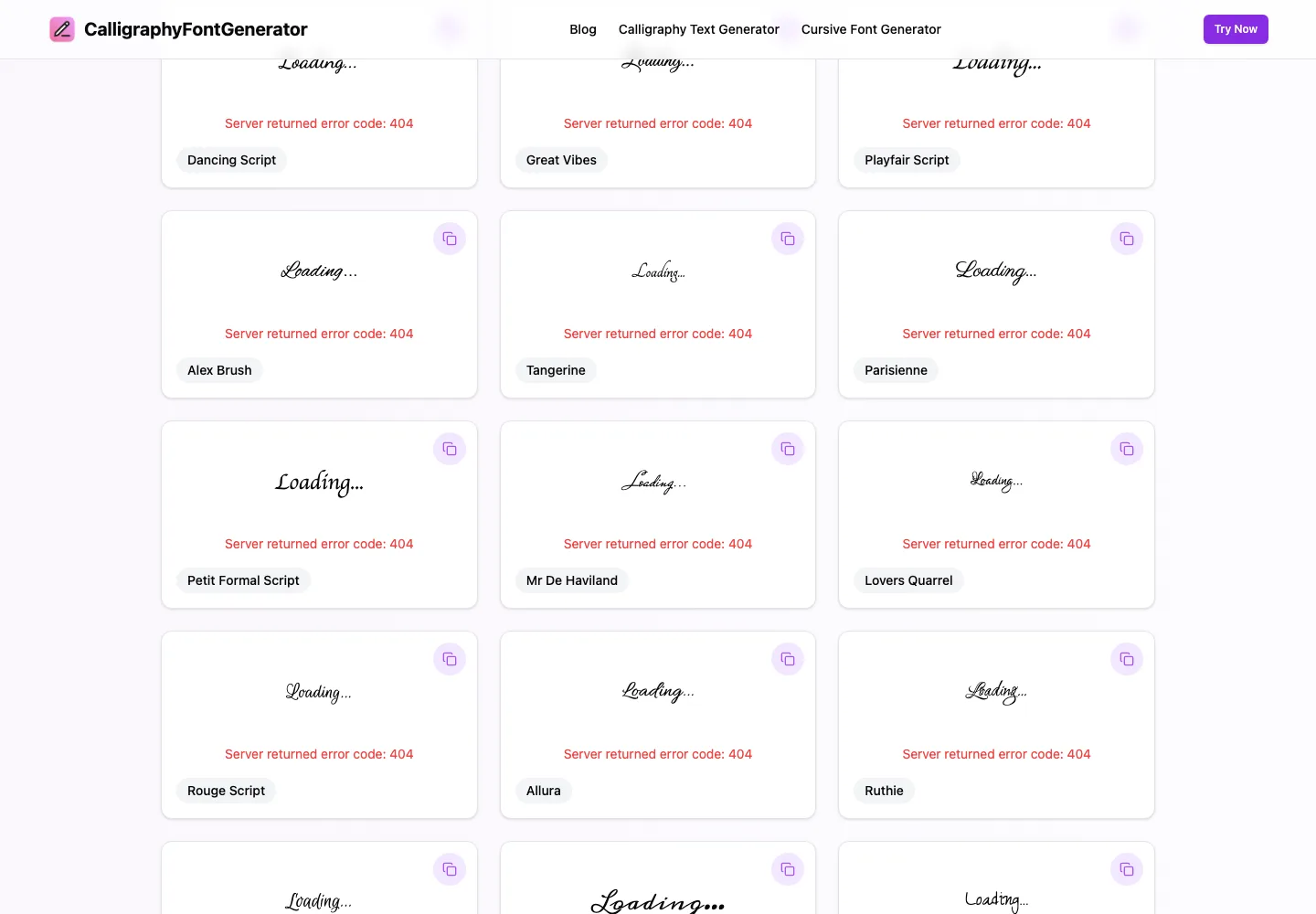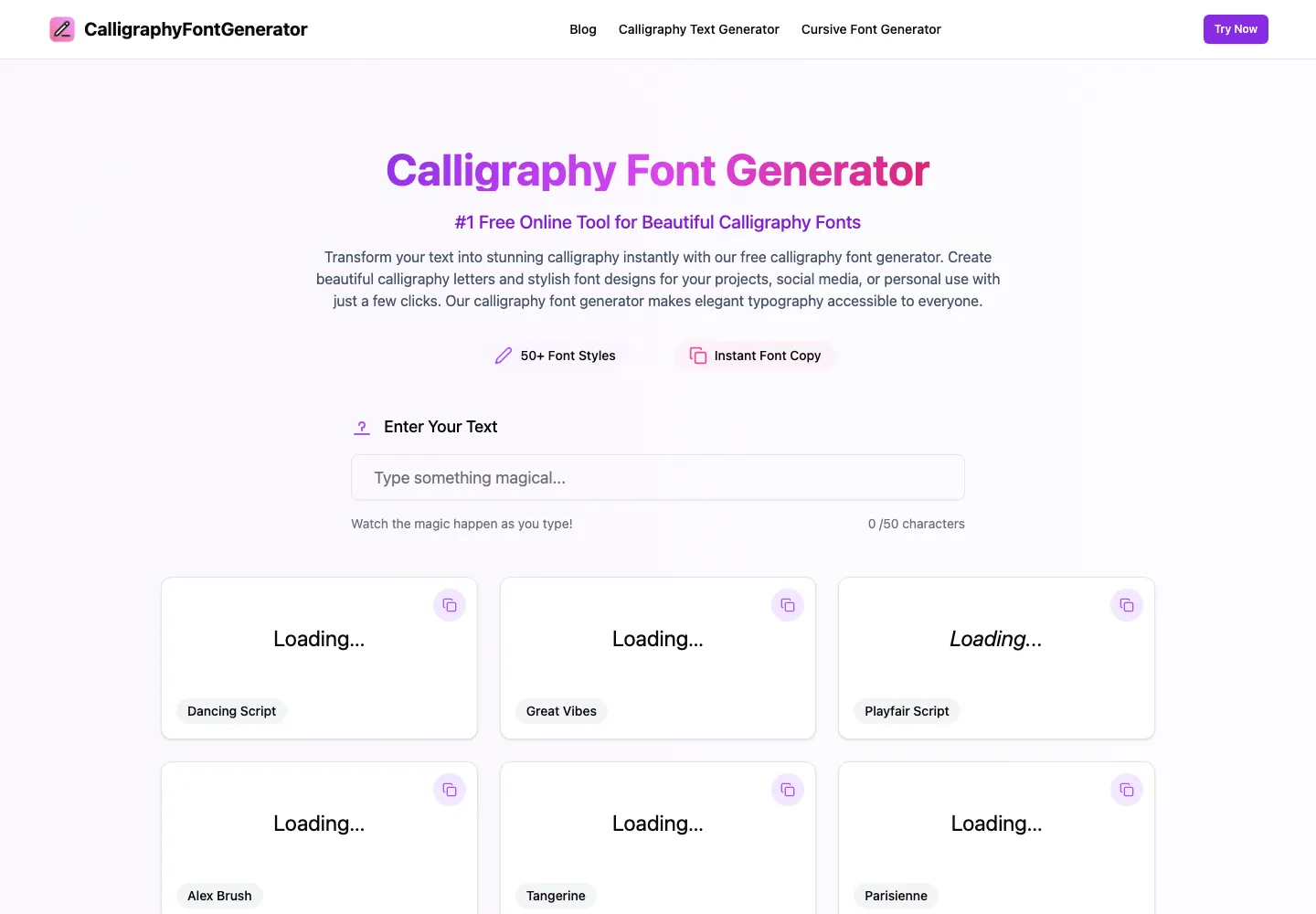
Calligraphy Font Generator 實測:字體全借自 Google Fonts
calligraphyfontgenerator.org 打著 50 多種書法字體、AI 推薦與圖片匯出的招牌,2026 年 9 月實測預覽功能整組 404,原始碼裡的字體清單只有 24 個,其中 23 個直接來自 Google Fonts。這篇整理實測經過、文案與程式碼的落差,以及直接去源頭下載字體的替代路線。
搜尋「書法字體產生器」,很容易撞上 calligraphyfontgenerator.org 這個站:招牌寫著 50 多種書法字體、即時預覽、PNG/JPG/SVG 匯出,還有 AI 字體推薦與簽名產生器。我在 2026 年 9 月 13 日實際打開它、輸入文字測了一輪,得到的結論跟文案落差很大:字體預覽功能整個是壞的,24 張預覽卡全部回 404 錯誤;文案寫的 50+ 字體,在它自己的程式碼裡只有 24 個;至於匯出圖檔、AI 推薦這些招牌功能,在整個網站公開的前端程式碼裡都找不到實作。
我打開網站輸入文字,24 張預覽卡全部回 404
實際使用的方式很單純:首頁有一個輸入框,上限 50 個字元,打完字之後,下方會展開一整排字體預覽卡,每張卡用不同字體渲染你輸入的文字,右上有 Copy 按鈕。流程設計本身沒問題,問題出在它此刻跑不起來。
我用瀏覽器實測,同一個下午試了首頁與兩個子頁面、多次重新載入,結果一致:預覽卡全部停在「Server returned error code: 404」的紅字,輸入什麼字都不會出現預覽。直接呼叫它背後的預覽 API,得到的也是 Apache 伺服器回的 404,代表這個 API 在伺服器端根本沒有在跑,與我這邊的網路環境無關。首頁還有另一個毛病:頁面載入時觸發 React 的編號 329 錯誤,運氣不好時整頁直接變成「Application error」白畫面,運氣好時互動區勉強活著,但字體卡一樣全壞。
Calligraphy Font Generator 字體預覽卡截圖,每張卡顯示字體名稱與 Copy 按鈕,卡內出現紅色 Server returned error code 404 錯誤文字,預覽停留在 Loading 狀態Pin
2026 年 9 月實測:24 張字體預覽卡全部停在 404 錯誤,輸入文字不會出現預覽(圖片來源:Calligraphy Font Generator 官網截圖)
預覽掛掉時,Copy 按鈕的行為也值得知道。從它公開的前端程式碼看,這個按鈕複製的內容有兩層:API 正常時複製轉換過的花俏文字,API 失敗時退回把你輸入的原文原封不動複製回剪貼簿。也就是說,現在按下 Copy,你只會拿回自己剛打的那幾個字,等於沒複製到任何東西。
就算未來 API 修好了,這類「複製文字」的產生器還有一個先天的上限:它複製出來的是文字內容,美麗的書法外觀取決於你貼過去的軟體有沒有安裝那套字體。把花俏文字貼進 WhatsApp 或 Instagram,對方看到的通常只是普通字型,因為那些 App 沒有 Dancing Script 這套字體可套用。要讓作品在任何地方都長得一樣,正解永遠是把成品輸出成圖片,或者拿到字體檔本體,而這兩件事這個站都做不到。
這裡要誠實畫一條線:以上是單一時點的實測結果。我在同一天多次載入、走不同頁面、直打 API,結論都一致,但站方什麼時候把伺服器修好,我不知道。如果你讀這篇文章的時間距離 2026 年 9 月已經很久,值得自己再開一次網站驗證,別把這篇的「現在壞了」當成永久判決。
文案寫 50+ 字體,程式碼裡的清單是 24 個
「50+」的字樣在首頁多處出現:統計卡寫「50+ Font Styles」,功能標題寫「50+ Elegant Fonts」,FAQ 也寫著「all 50+ fonts」。但把網站載入的 JavaScript 檔案抓下來看,字體清單是一個寫死的陣列,編號從 1 排到 24:Dancing Script、Great Vibes、Alex Brush、Tangerine、Parisienne,一路到 Sacramento,中間沒有動態載入的第五十個。頁面實際渲染出來的預覽卡,也確實就是 24 張。
Calligraphy Font Generator 官網首頁截圖,標題寫著第一名的免費線上書法字體工具,宣稱 50 以上字體風格,下方為文字輸入框與字體預覽卡Pin
官網首頁掛著 50+ Font Styles 的招牌,實際字體清單是 24 個(圖片來源:Calligraphy Font Generator 官網截圖,2026 年 9 月)
24 個裡面還有一個特別的:「Playfair Script」。這個名字在 Google Fonts 查不到對應字體(API 直接回 400),而網站自己的樣式表把它對應到 Playfair Display 這個襯線字體的斜體。換句話說,那張卡片顯示的既不是它宣稱的名字,也不太算書法字體。
其他招牌宣稱也對不上。首頁的功能區塊列了 PNG/JPG/SVG 多格式匯出、AI 字體推薦、簽名產生器、字體配對工具,FAQ 還說註冊帳號能收藏字體。我把整個網站公開的前端程式碼全部掃過一遍:沒有任何下載圖片或轉 SVG 的程式碼,沒有任何推薦邏輯,簽名與配對也沒有對應頁面,站內地圖總共 18 條網址,沒有一條是這些功能。註冊入口同樣不存在,login、signup 這些路徑全是 404。服務條款裡寫的帳號、付款、退款,在站上找不到任何對應的東西。
網站宣稱實測與原始碼
50+ 種書法字體清單寫死 24 項,其中 1 項對不到真實字體
PNG/JPG/SVG 匯出前端程式碼與站內頁面都找不到實作
AI 字體推薦無推薦邏輯,無對應頁面
簽名產生器、字體配對工具無對應頁面
註冊帳號收藏字體無任何註冊入口
數千名滿意用戶見證見證者引言把站名叫成 CalliGen Pro,與站名不符
見證區那個細節值得一提:四位用戶的推薦語排版整齊、姓名都是常見英文名,其中一位「小型企業主」的引言裡,把工具稱為 CalliGen Pro,這個名字在站上其他任何地方都沒出現過。模板文字抄來抄去忘了改乾淨,大概是最好解釋。
24 個字體裡有 23 個,直接去 Google Fonts 免費拿
把清單裡的 24 個字體名稱逐一拿到 Google Fonts 比對,23 個命中,全是免費字體庫裡的現貨,多數歸在 Handwriting(手寫)分類。抽查其中幾個的授權檔,Dancing Script、Great Vibes、Caveat、Lateef 都是 SIL Open Font License:可以免費商用、可以安裝到任何軟體、可以嵌入文件,幾乎沒有附帶條件。網站 FAQ 說「所有字體皆授權可供個人與商業使用」,這句話的真相其實是:字體本來就是 Google Fonts 的開放授權字體,站方只是把它們包了一層預覽,授權要回 Google Fonts 的字體頁面查才算數。
對台灣讀者來說,還有一個比功能壞掉更根本的限制:這 24 個字體全部只覆蓋拉丁字母(部分額外支援阿拉伯文、越南文或西里爾文),沒有任何一個含中文字。在輸入框打中文,畫面只會退回你系統的預設字體。想找中文書法字體的人,這個站從根上就幫不上忙,方向應該轉向中文字體資源,例如我們介紹過的 FreeFont 免費可商用字體庫,或走開源字型路線的 Velvetyne Fonts。
一個 48 小時專案,怎麼長成搜尋結果裡的免費工具
這個站的來歷,公開資料其實拼得出輪廓。網域在 2025 年 5 月 9 日註冊。兩週後,波蘭社群網站 Wykop 出現一篇自介文,作者描述自己用 Next.js 加 Tailwind 在大約 48 小時內做出了這個書法字體產生器,動機寫得直白:SSR 對 SEO 是必備。那篇貼文裡還留下一個有趣的痕跡:文末附了一整段「為什麼這篇貼文會有效」的說明,從語氣策略到「把連結自然地放進描述」都寫得清清楚楚,看起來是把 AI 生成的行銷草稿整段貼上時,忘了刪掉給自己看的註記。同一個作者帳號在開發者社群 dev.to 也發過配套的導流文,文內宣稱「研究顯示使用自訂字體的貼文互動率最多高出 40%」,這個百分比查無出處。
變現方式也看得到。頁面裡掛了彈出式廣告腳本,廣告商的網域目前用公共 DNS(例如 Google 的 8.8.8.8)也查不到任何紀錄,等於連廣告都放不出來;頁尾則互連著一排同類型的工具目錄站,彼此收錄、互相導流。站內地圖也留下了推廣的軌跡:18 條網址裡,除了首頁、兩個換皮的同功能頁、幾篇部落格文章與法律文件,還有四條專門給目錄站驗收用的推薦頁,分別對著不同的收錄平台。服務條款與隱私權政策是另一組模板:條款細寫帳號註冊、付款與退款規則,但前面提過,站上既沒有帳號系統也沒有任何收費功能,文件與產品完全脫節。
把這些線索放在一起,這個站的長相就清楚了:個人開發者的 SEO 副業專案,用一週末的工時包裝一批現成的開放授權字體,靠搜尋流量與廣告變現。這不是什麼稀奇的罪過,但它解釋了為什麼文案會寫得比產品大那麼多,也解釋了伺服器壞掉之後,大概沒有專職團隊會立刻修。下次在搜尋結果裡看到功能列表特別滿、見證特別整齊、條款特別通用的免費工具站,可以直接檢查三件事:數字對不對得上原始碼、功能有沒有對應頁面、見證有沒有露餡。
想要書法字,更省時間的三條路
英文字母的書法字,直接去 Google Fonts。在分類裡勾 Handwriting,輸入自己的文字現場預覽,選定後下載字體檔安裝,Office、Illustrator 都吃,Canva 則是直接從內建字庫選。這篇文章列過的那 24 個名字,本身就是一份現成的懶人包清單。
需求換成中文字體的話,走免費可商用的中文字體資源。中文書法字體的合法免費來源比英文少,但 FreeFont 這類整理過授權的字庫,或 Velvetyne 的開源字型,都比一個不支援中文的英文產生器切題。
結論:字體去源頭拿,這個站等修好再說
給一個可以帶走的判斷:calligraphyfontgenerator.org 此刻是一個預覽功能全壞、文案與產品落差很大的包裝站,它包裝的字體本身乾淨合法,但那些字體你本來就能從 Google Fonts 免費拿到更好的版本。急著用字體的人,跳過它直接去源頭;已經把它加進書籤的人,可以等伺服器修好後再回來看一眼,順便重算一次它到底提供幾種字體。
這篇的實測基準日是 2026 年 9 月 13 日,單日多次實測與原始碼比對的結果都一致,文中的每一個結論,都來自你現在打開瀏覽器就能重複驗證的公開頁面與公開程式碼。網站狀態與字體清單都是會變動的東西,你使用的當下,請以現場看到的為準。